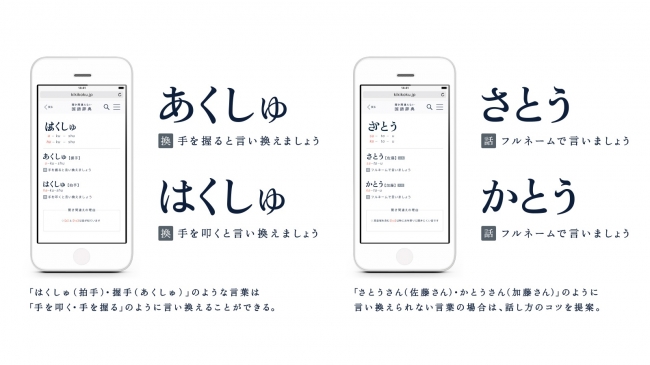
Talking Aid Project
言いたいことも言えないこんな世の中が「POIZON」。言おうとしたことと違ったことを言ってしまうのが「言いまつがい」。そして聞き取りにくい「聞きまつがい」をなくしていくのが「Talking Aid Project」だ。この活動で志村けん扮する「ひとみばあさん」にも言葉が聞き取りやすい「あんだってー?」と言わない社会が訪れそうだ。
2017年3月3日の「耳の日」に難聴の人が聞き取りやすい言葉に満ちた「言葉のバリアフリー」社会を目指してパナソニック株式会社が開始したのが「Talking Aid Project」。
「Talking Aid Project」は、高性能補聴器を提供しているパナソニック補聴器株式会社と協力して推進する、話し手に着目し、難聴の人にも聞き取りやすい言葉や話し方を広める活動。
聞き間違えない国語辞典
活動の一環で、株式会社三省堂と聞き間違えやすい言葉の言い換えや発音のコツを掲載した無料のデジタル辞書『聞き間違えない国語辞典』を共同開発した。
『聞き間違えない国語辞典』には、聞き間違えの頻度の高さを判定するAIプログラム「Talking Aid AI」によって抽出された言葉がおよそ150万組収録している。
聞き間違えやすい言葉の言い換え、また言い換えが難しい場合の話し方のコツなどを提案してくれ、同時に聞き間違えやすい言葉を「見える化」する独自フォントも開発した。
「聞きまつがい」の次は、是非とも、「書きまつがい」を自動修正してくれるAIがも開発してほしい。
▼ 「Talking Aid Project」独自フォント
複数の音の組み合わせをどちらとも読めるフォントで「見える化」し、聞こえの問題を視覚的に理解できるようにした。このフォントを通じ「聞こえの問題」と「話し方」に新しいイノベーションを起こしていく。
▼『聞き間違えない国語辞典』
三省堂の「スーパー大辞林3.0」の総項目のうち約25万語から、聞き間違えやすい言葉の言い換えや発音のコツを集めた無料のデジタル辞書。
▼ききまつがいが起こりやすい言葉をmojiru風に「見える化」してみた。